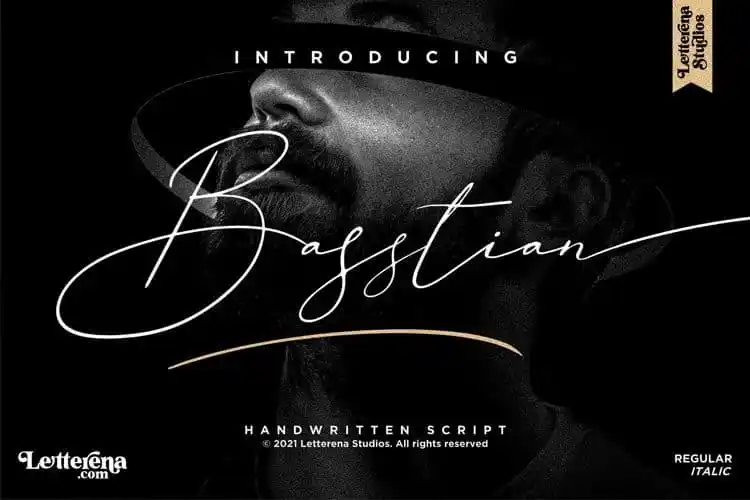
Basstian Script Font – Download Grátis
A Basstian Script Font é uma fonte escrita a mão criada por Letterena Studios, perfeita para uma variedade de projetos que valorizam personalidade e delicadeza. Suave e envolvente, ela transmite um toque elegante e autêntico, tornando-a ideal para criações como logomarcas e embalagens de produtos, design de decoração casada à medida, lembranças de festa, etiquetas em geral e até mesmo para fotografias. Sujeira cuidadosamente introduzida dá ao texto uma textura única que se assemelha a uma assinatura, garantindo um toque autêntico aos seus projetos. Seja você trabalhando com materiais de embalagem, design gráfico ou até mesmo para criar designs únicos e personalizados para sua marca – esta fonte oferece o tom perfeito que enriquecerá seu trabalho. Com uma ampla gama de aplicabilidades, a Basstian Script é uma escolha valiosa para quem valoriza um toque delicado em seus projetos.